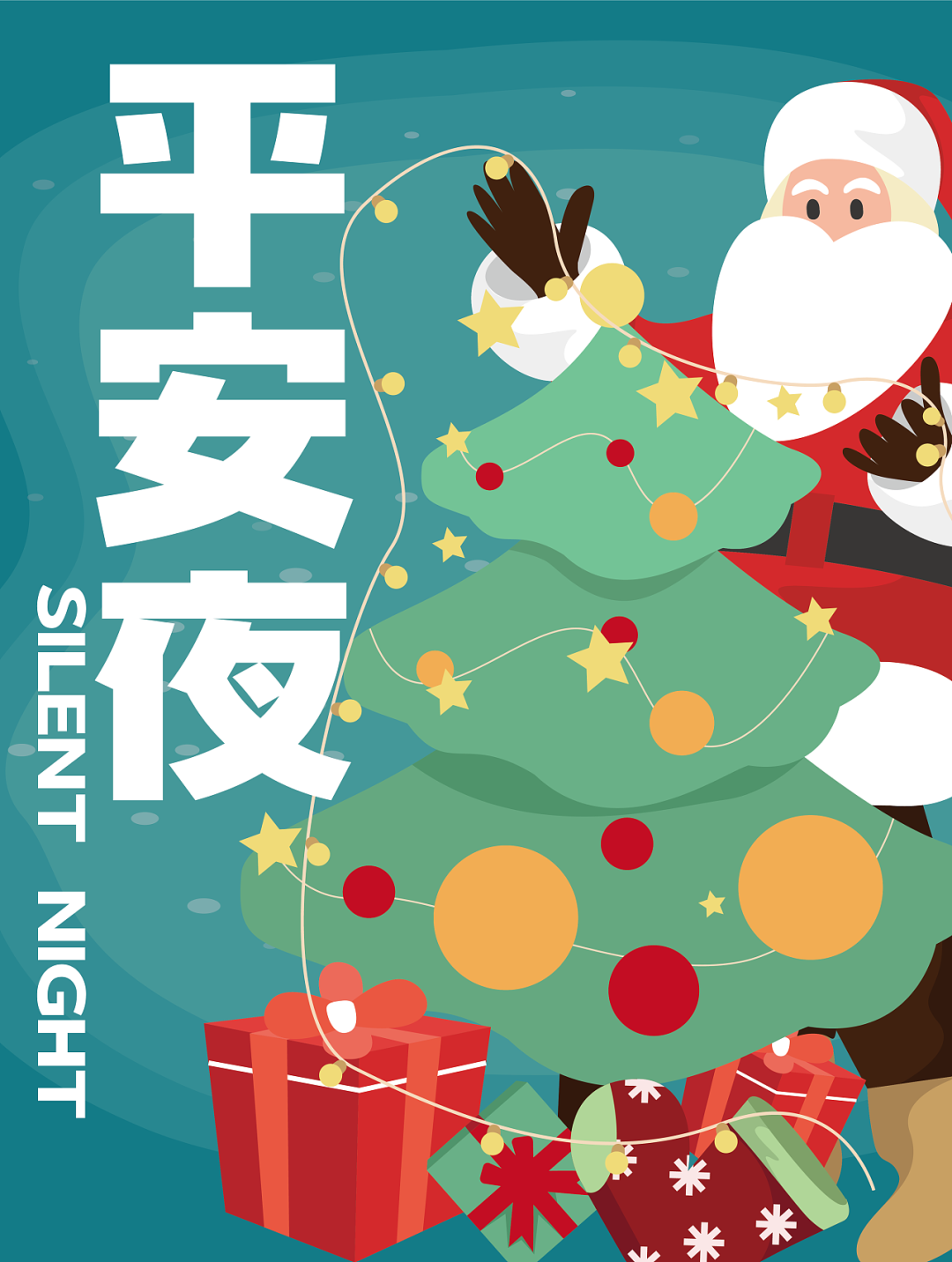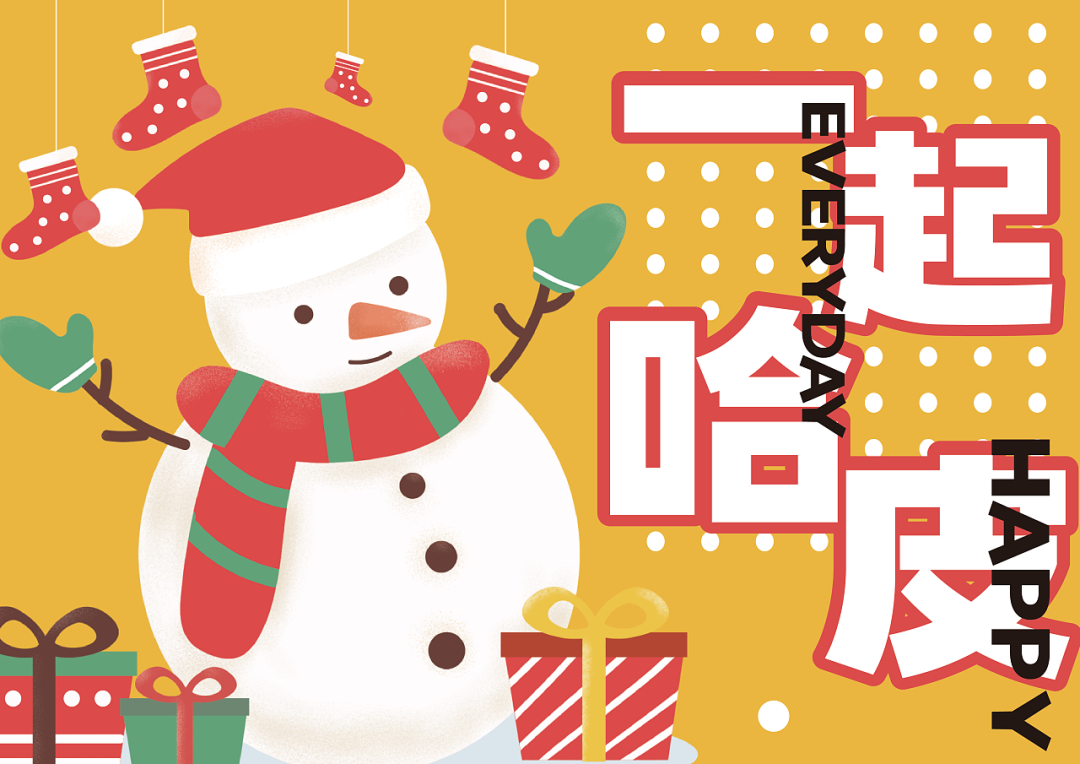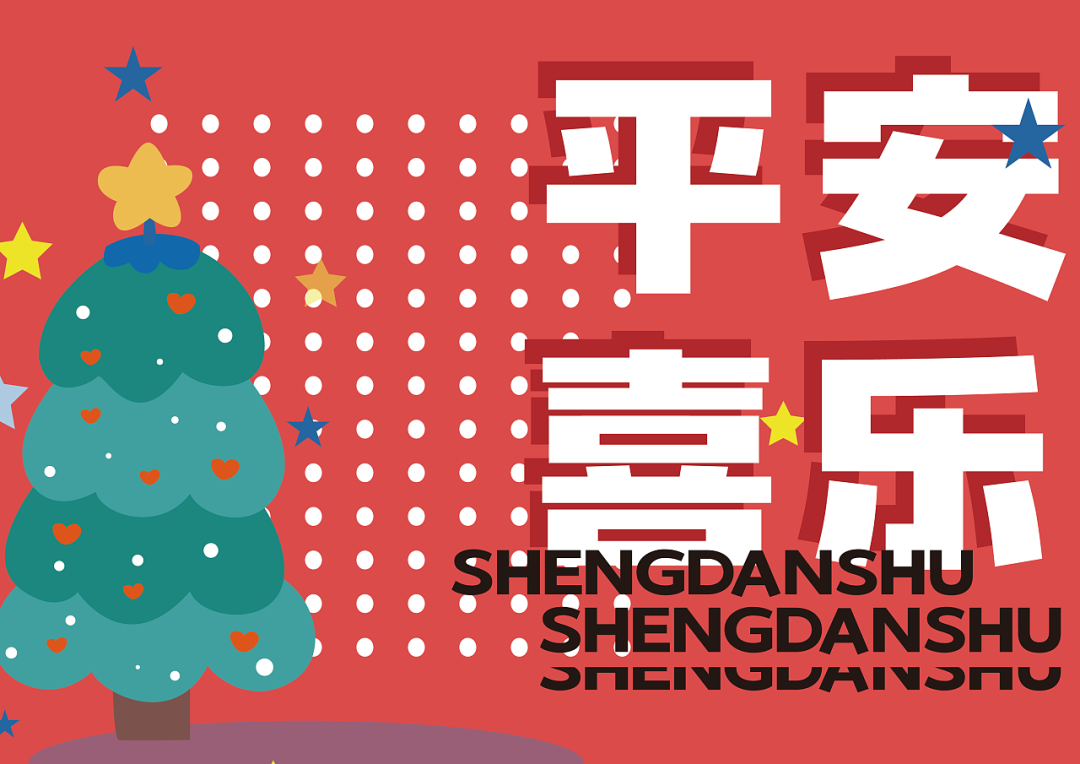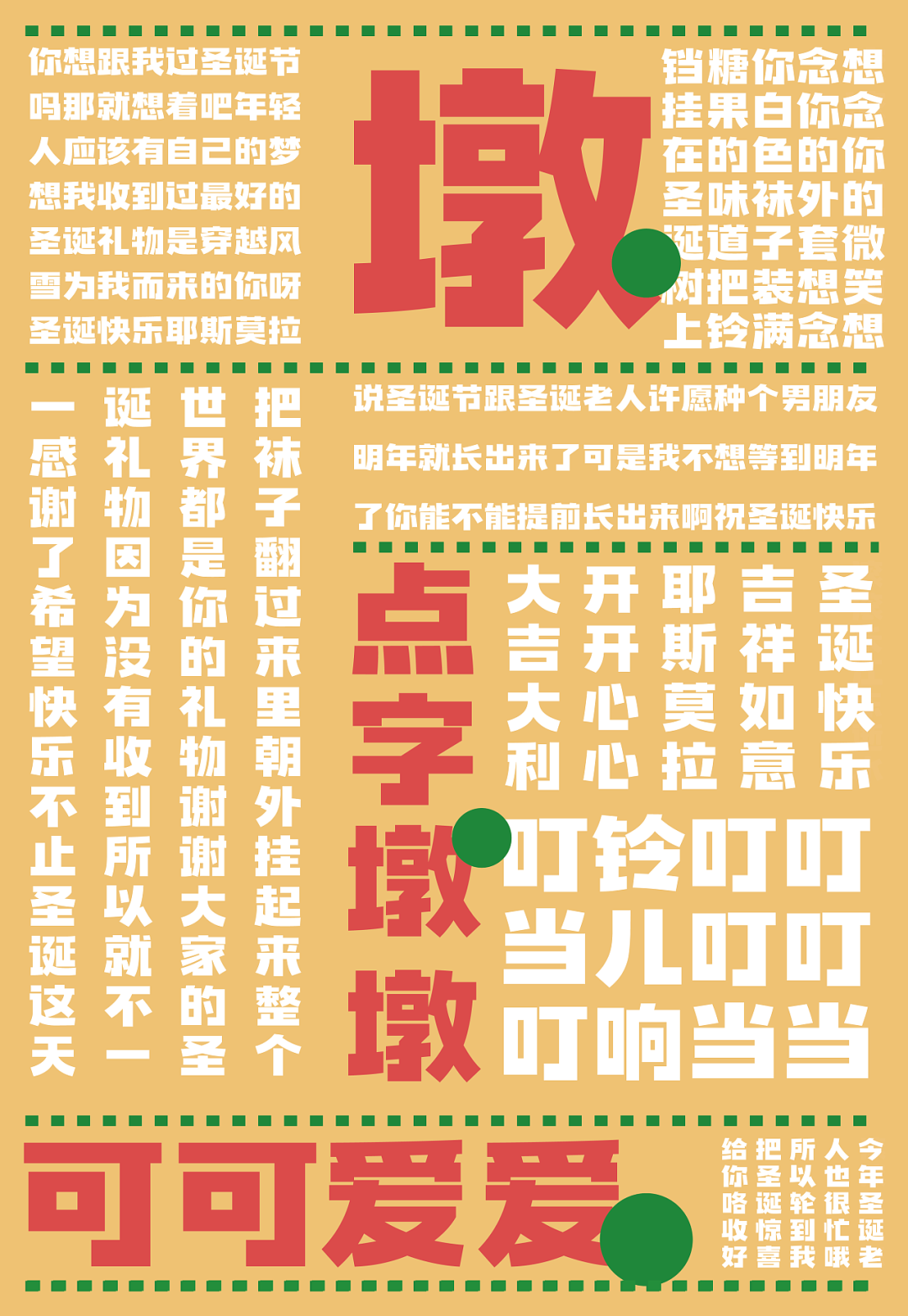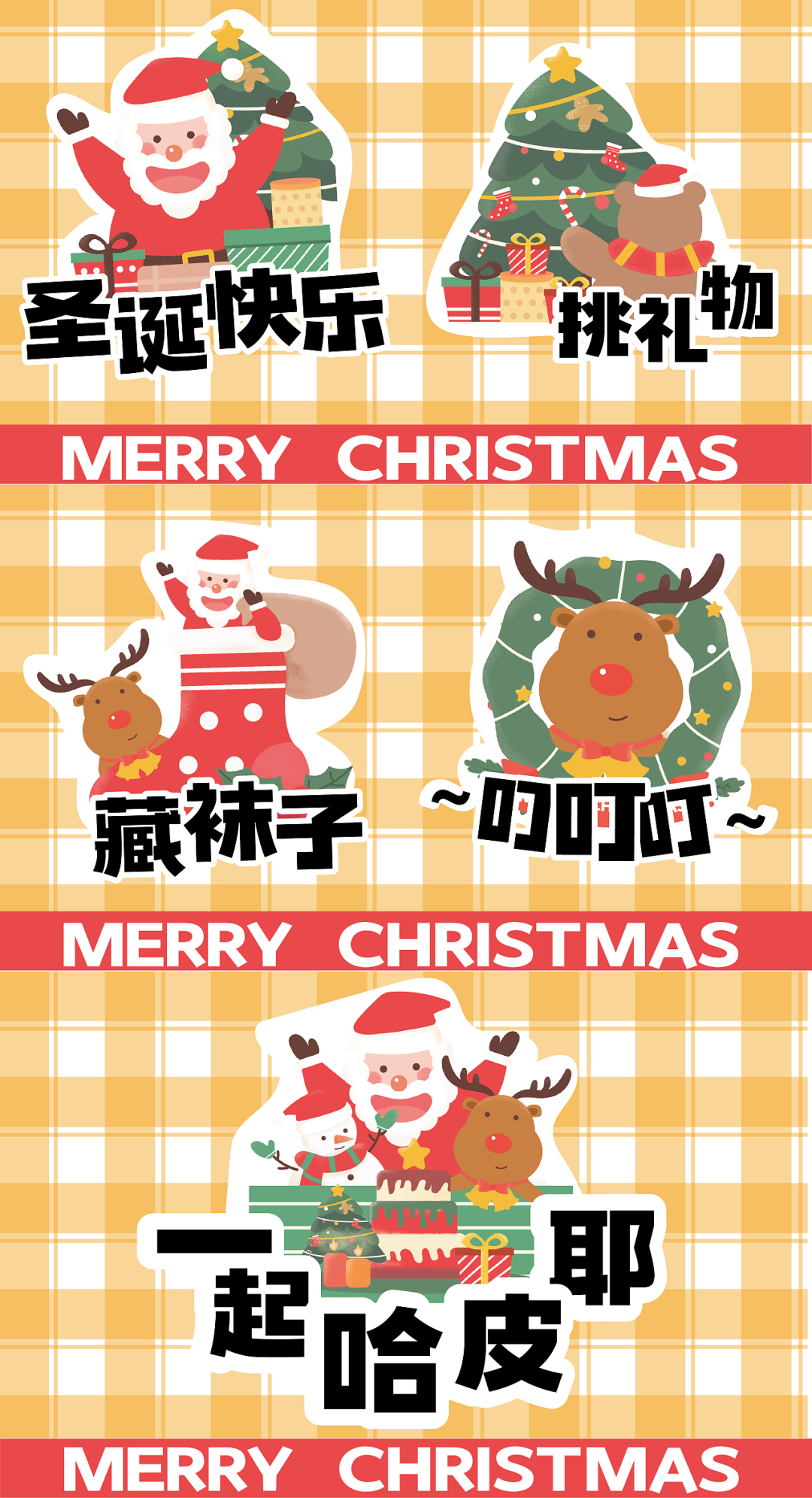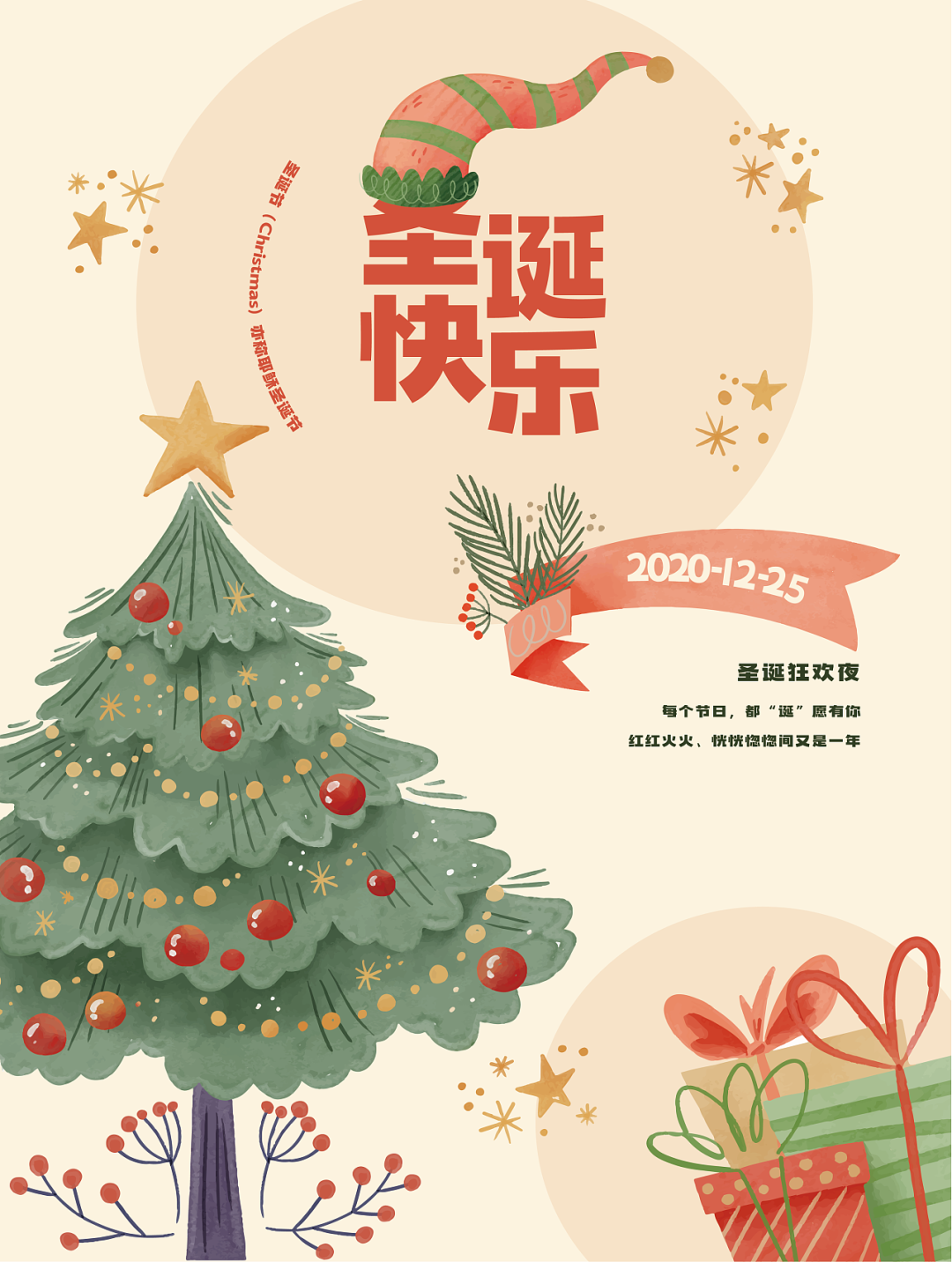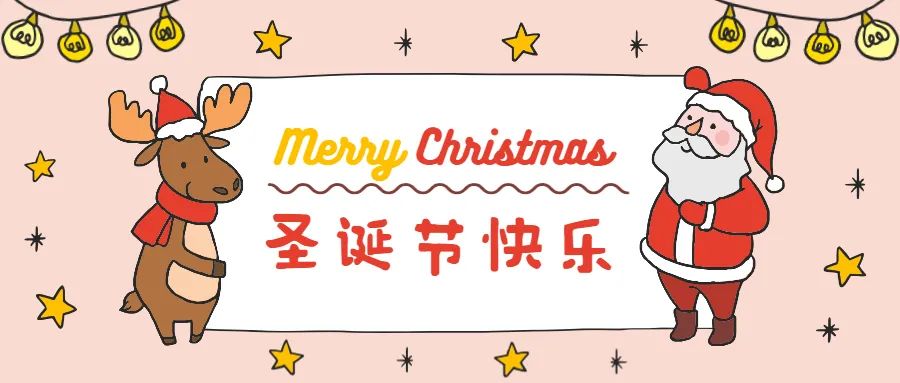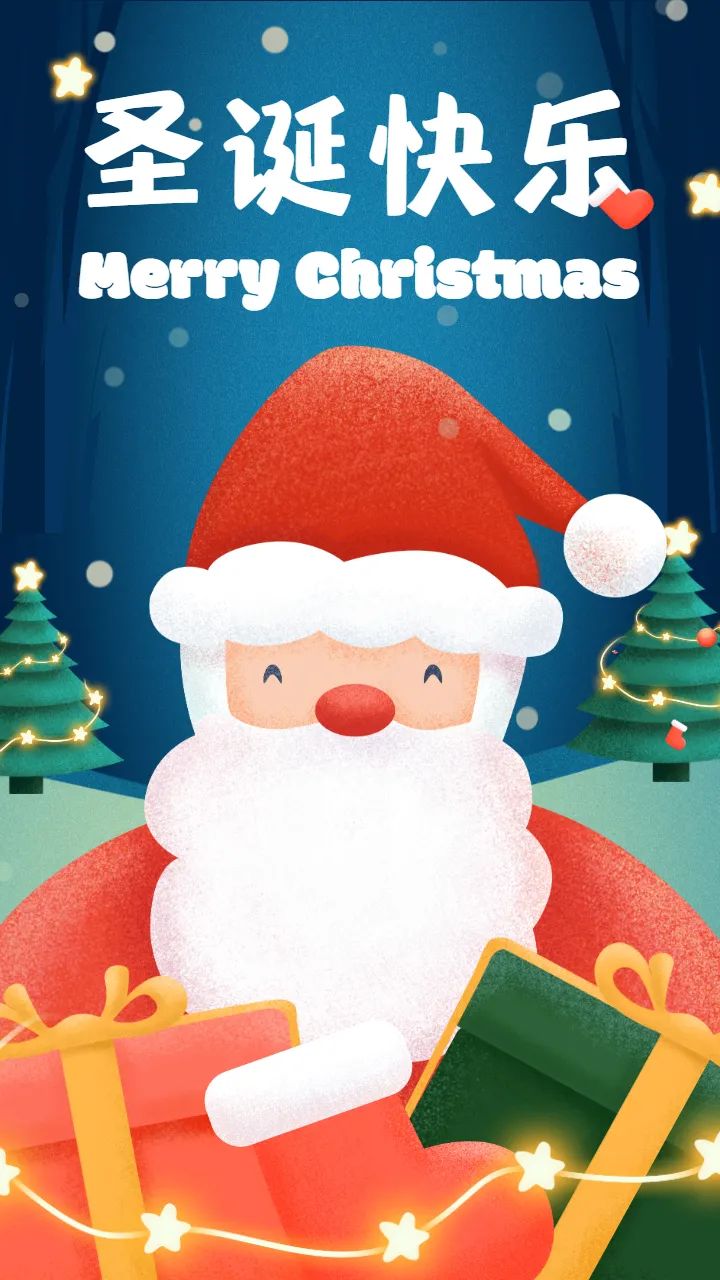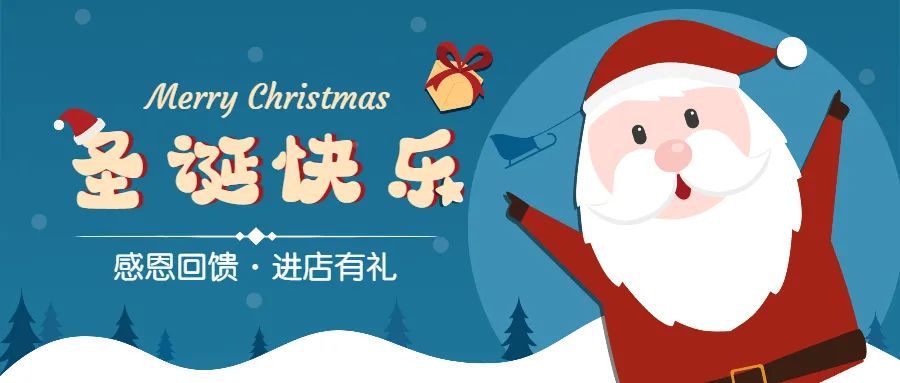
想过好圣诞的打工人,都默默收藏了这波字体~
下周就是圣诞节了,不知道你的双蛋海报做完了没?你不说还好,你一说就自闭……
不过没关系,借势海报没那么难,只要营造好气氛就行,今天就给推荐一波字体。
首先是我们可爱又好用的会员字体——点字墩墩体,之前在教程中也用过它,它最大的特点就是憨态可掬,很有亲和力,适用于任何场景~
还有它的一众“团友”,都是走可爱路线,比如点字奇妙体、点字焦糖体、点字QQ糖、点字童稚体。
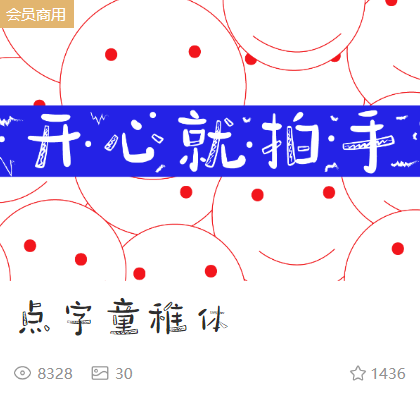
如果不想走卡通风,也可以选择醒目的标题字,比如点字大字报、点字倔强黑。